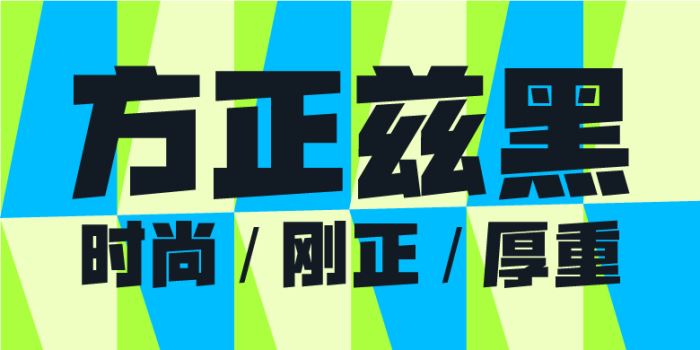
方正自留宋家族由方正字库陈宇设计师出品的艺术字体,字体笔画粗壮,重心平稳,字面饱满,风格时尚、刚正、厚重,分量感十足,适合应用于艺术设计、平面宣传设计、网页设计,书法等领域。
方正兹黑是一款偏重于装饰性的创意黑体,这款字体笔画粗壮,重心平稳,字面饱满,风格时尚、刚正、厚重,分量感十足,打破传统的“横平竖直”,巧妙利用负形增加字体的动感,有古老石碑的拓印之风,不失时尚潮流的文艺之美,无论是横排或竖排,行列之间整齐有序,可广泛用于报纸、杂志、包装、广告等印刷品的标题、正文。